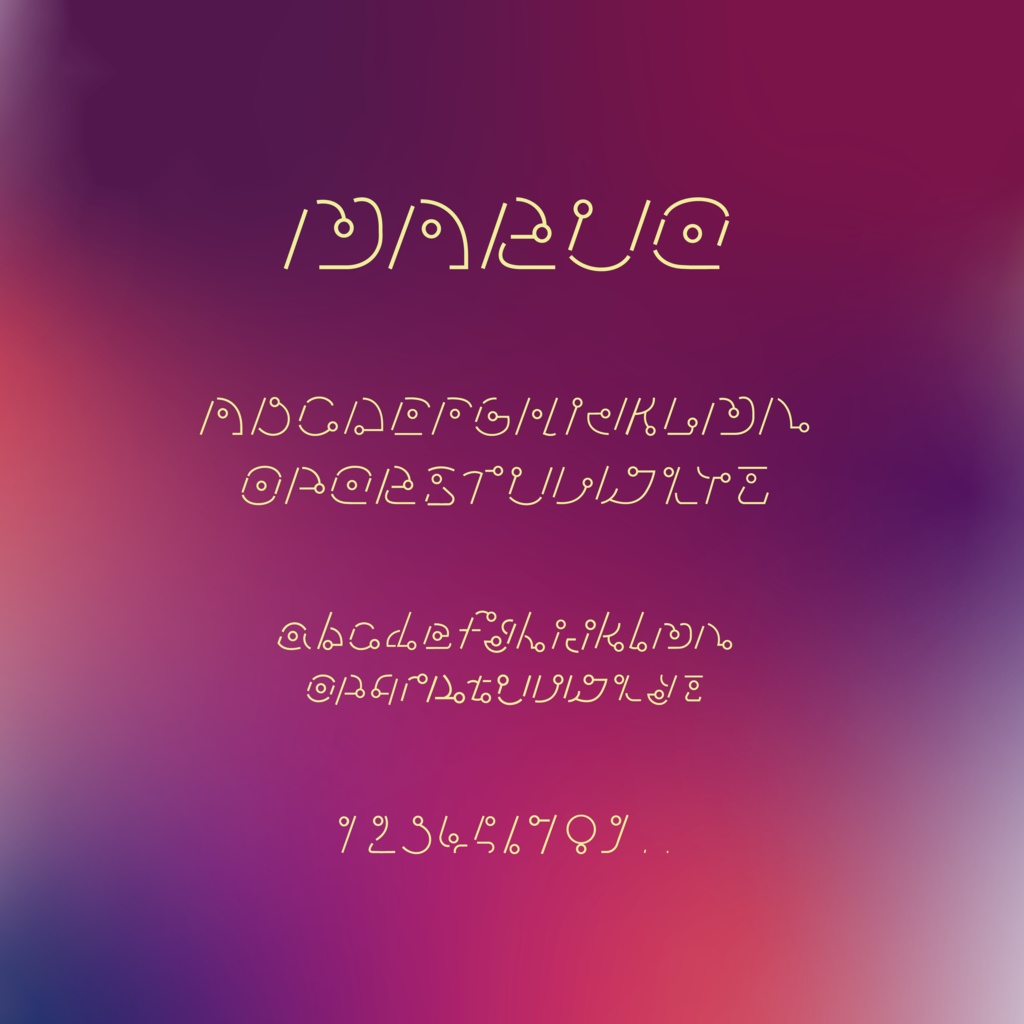
【フリーフォント】 MARUQ
宇宙・SF・地球外生命体・でもかわいい がテーマのフリーフォントMARUQです。 デザイン性を重視しているため可読性は低いです。 ポスター・サムネイル・動画・本の表紙・ゲーム・ロゴ...など様々な用途で利用できます。 【収録物】 アルファベット全種(大文字・小文字)・数字・ピリオド・カンマ 【利用規約】 NG フォントデータの改変含む再配布・複製 OK 常識の範囲内での利用 利用報告などは不要です。ご自由にお使いください。 フリーフォントですが、作者の著作権は放棄しておりません。 DL後の不具合などのサポートは行っておりません。 ご使用の際は全て自己責任でお願いいたします。 今後フォントのアップデートが入る可能性もあります。 WEBサイトにて試し打ちが可能です(フォントサイズ固定)。 ▷http://poppo.jellybean.jp/maruq_web/